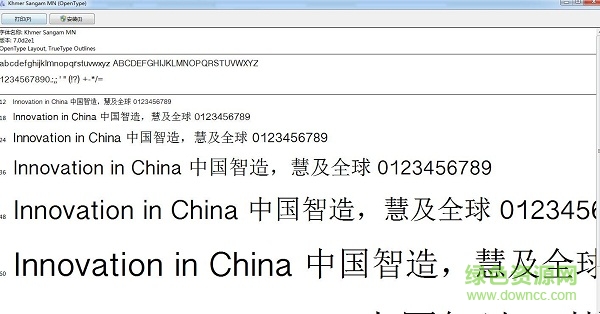
khmersangammn字體是一款高棉語無襯線字體,布白均勻,筆法挺勁,字面干凈大氣,閱讀效果好,綠色資源網(wǎng)匯聚海量精美好看的無襯線字體,全部免費提供,歡迎下載!
高棉語的文字最初來源于印度南部,公元1世紀(jì)柬埔寨建國后,在印度古代婆羅米字母的變體帕拉瓦字母的基礎(chǔ)上改造而成。
現(xiàn)代高棉語標(biāo)準(zhǔn)音建立在金邊方言的基礎(chǔ)上,它沒有聲調(diào),共有20個輔音,8個短元音,10個長元音以及13個復(fù)合元音.不同的方言有著不同的元音和輔音數(shù)量